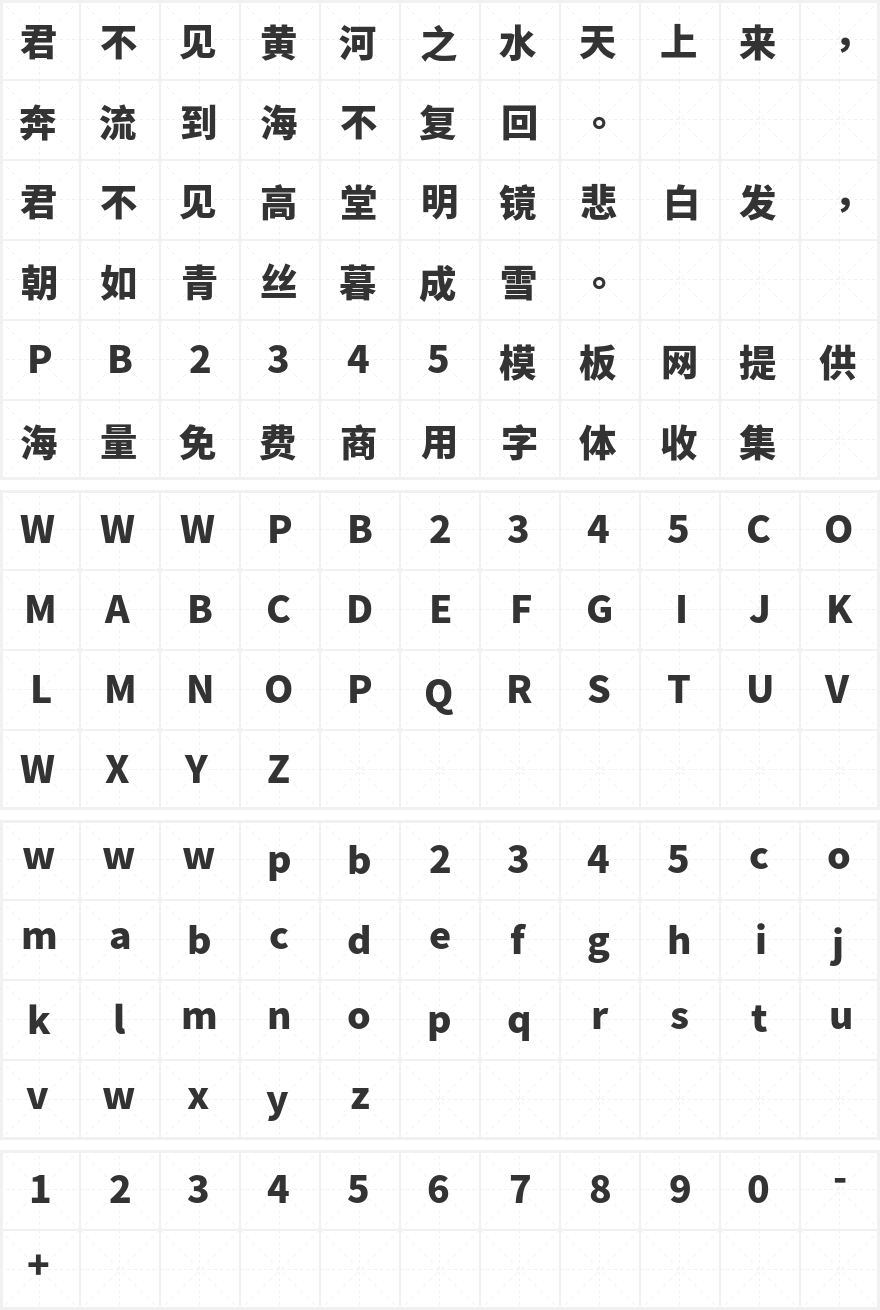
思源黑体 SourceHanSansSC-Heavy
思源黑体 SourceHanSansSC-Heavy 字体介绍
思源黑体 SourceHanSansSC-Heavy 是由 Adobe 与 Google 联合开发的思源黑体系列中的特粗字重变体,属于该家族 “极细(ExtraLight)至特粗(Heavy)” 七级字重体系里的 “视觉强调型” 字体。名称里的 “SC” 代表简体中文版本,“Heavy” 直接体现其粗壮的笔画特征;在 Google 对应的 “Noto Sans CJK” 系列中,这个字重的名称是 “Black”,核心设计风格和 Adobe 版本保持一致。
一、核心设计特点
1. 强视觉冲击力的笔画设计:作为思源黑体中最粗的字重之一,它的笔画宽度明显增加,线条扎实饱满,没有多余装饰,既保留了无衬线字体的现代简洁感,又通过加粗的笔触增强了文字的 “视觉重量”—— 在页面中能快速吸引读者注意力,同时笔画边缘平滑规整,不会因为过粗而显得臃肿或模糊。
2. 延续家族的多语言适配优势:单个字体文件包含超过 65535 个字形(满足 OpenType 字符量上限),全面覆盖简体中文(包括常用字和生僻字)、繁体中文、日文、韩文等东亚核心语言,还兼容拉丁语、希腊语、西里尔文等西方字符集。针对不同地区的用字习惯(比如中日韩对部分汉字的字形差异)做了细节优化,能实现多语言排版时的风格统一。
3. 跨媒介显示优化:虽然笔画粗壮,但设计时充分考虑了屏幕与印刷的差异 —— 在电子屏幕(如手机、电脑、户外显示屏)上,能减少像素压缩导致的 “糊边” 问题;在印刷场景(如海报、横幅、书籍封面)中,加粗的笔画不容易因为油墨扩散丢失细节,兼顾了不同媒介的可读性与美观度。
三、适用场景与设计价值
凭借 “特粗” 的视觉属性,SourceHanSansSC-Heavy 特别适合需要 “突出重点、强化记忆” 的场景,具体包括:
• 视觉焦点类设计:海报主标题、广告标语、户外广告牌文字、品牌 LOGO 中的核心文字,通过粗壮的笔画增强信息穿透力,让受众快速捕捉关键内容;
• 界面与导航设计:网页或 APP 中的一级导航栏、按钮文字、警示信息,用特粗字体区分层级,帮助用户快速识别功能入口;
• 印刷与出版场景:书籍、杂志的封面标题、章节大标题、画册中的重点注解,通过和正文(常规 / 细字重)的对比,优化排版层次感,提升阅读体验;
• 商业物料制作:产品包装上的品牌名、促销活动中的 “限时优惠” 等强调性文字,用特粗字体强化视觉吸引力,刺激用户关注。
四、与家族其他字重的差异
在思源黑体的七级字重体系中,SourceHanSansSC-Heavy 定位 “视觉强调”,和其他字重有明确的功能划分:
• 对比 “Regular(常规)”“Bold(粗体)”:它的笔画更粗,视觉冲击力更强,不适合长文本排版(容易显得压抑),只用于重点内容;
• 对比 “ExtraLight(极细)”“Light(细体)”:两者是完全相反的视觉属性,前者适合轻量化、优雅感的设计,后者则专注 “醒目、有力” 的表达;
• 实际应用中,常和其他字重搭配使用(比如 “Heavy 标题 + Regular 正文”),通过字重差异构建清晰的信息层级,让排版既有序又有视觉张力。